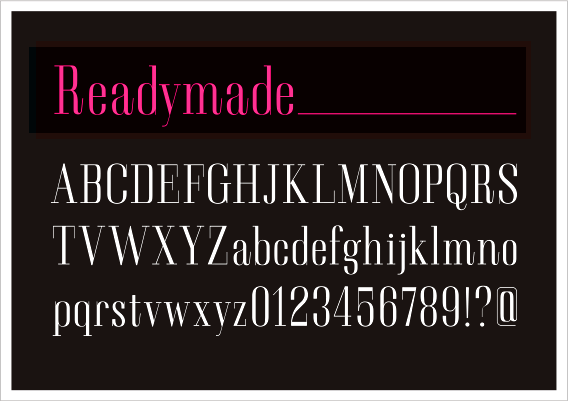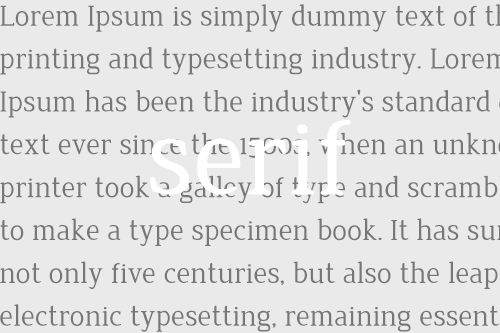
おすすめの欧文セリフ体フォント4選
欧文フォントにはフォントの端に飾りがある「セリフ体」と飾りがついていない「サンセリフ体」があります。今回はセリフ体の中でおススメのフォントをご紹介します。セリフ体を使えばエレガントな印象も可能です!
Mikiyu Font alphapen
みきゆフォントのアルファペンバージョン。アルファベット、数字、記号が収録されています。
Romance A
女性向けのフリー素材を配布しているAsterismが提供しているエレガントなビットマップフォント。
Romance B
上記と同じビットマップフォント。白抜き文字になっています。
レディメイド
欧文のフリーソフト。オシャレな雰囲気にしたいときにおすすめです。